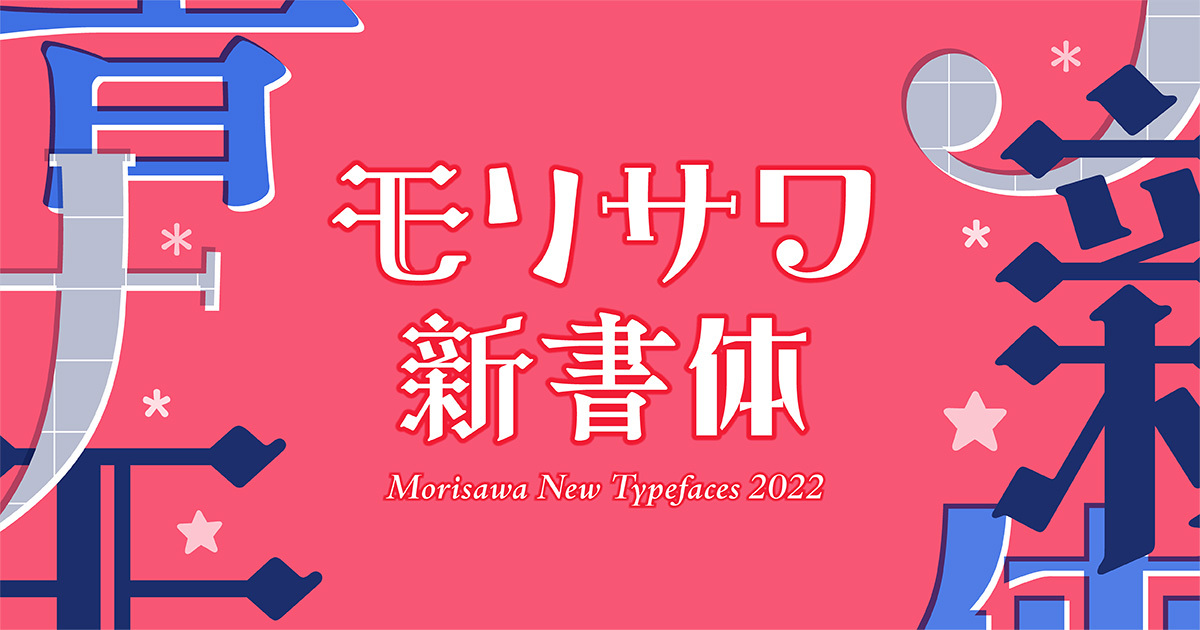
モリサワが10月26日(水)11時から2022年新書体の提供を開始。2022年新書体の特設ページが9月27日に公開
モリサワは、2022年10月26日(水)11時から「Morisawa FontsおよびMORISAWA PASSPORT アップグレード2022年10月版」として2022年新書体の提供を開始することを発表した。
「Morisawa FontsおよびMORISAWA PASSPORT アップグレード2022年10月版」では、合計77ファミリー500書体以上に及ぶ、過去最大の書体数が登場。
和文書体では『インパクト』『ゆるポップ』『ロマン』『オールド』の4つのジャンルで個性的なデザイン書体などを強化するほか、欧文書体も『オーガニック&ディスプレイ』『クラシカル&スタンダード』『Roleスーパーファミリー』『Clarimo UDシリーズ』の4ジャンルを一挙にリリースする。
また、「秀英四号太かな」を「秀英初号明朝」の漢字と合わせて総合書体化した「秀英四号太かな+」や、ユニークでどこか懐かしい書体「ヒラギノ丸ゴ オールド」も登場。
さらに今回の新書体提供にあわせて、「リュウミン」、「ゴシックMB101」、「すずむし」をはじめとした人気書体のAP版や、「G2サンセリフ」の文字セット追加、定番書体「こぶりなゴシック」のウエイトも追加される。
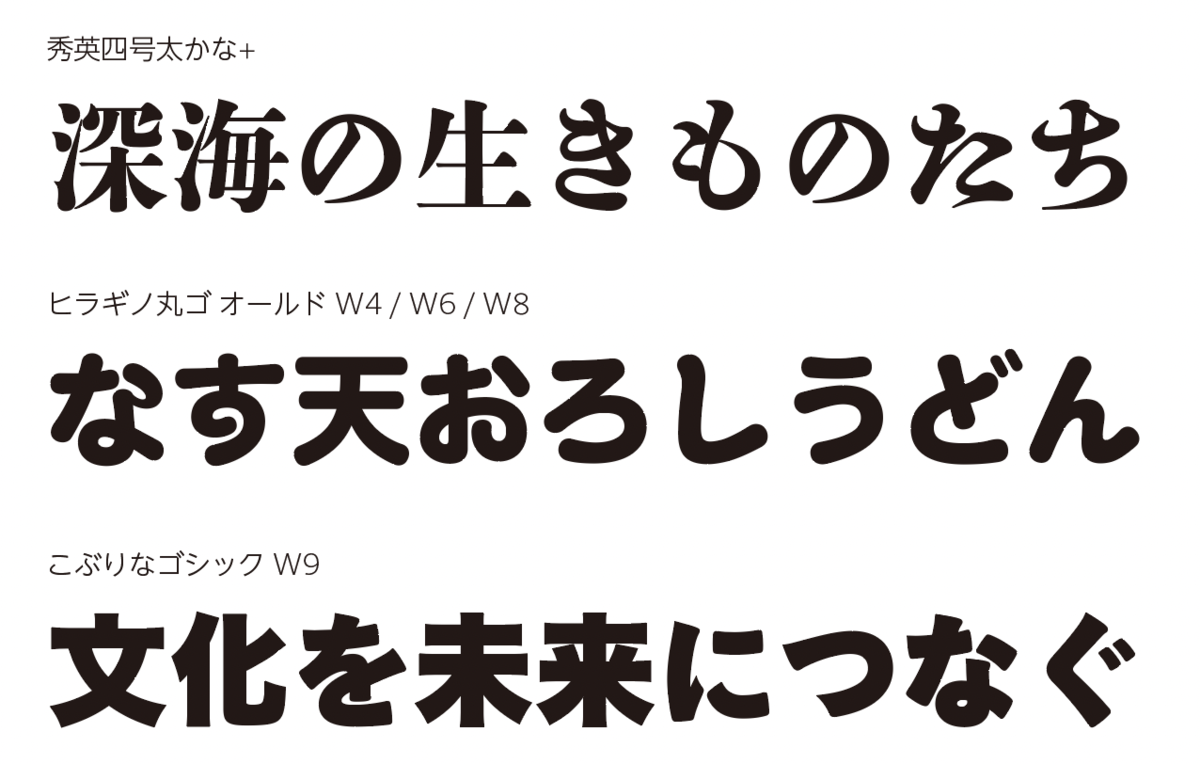
モリサワ2022年新書体特設ページが9月27日に公開
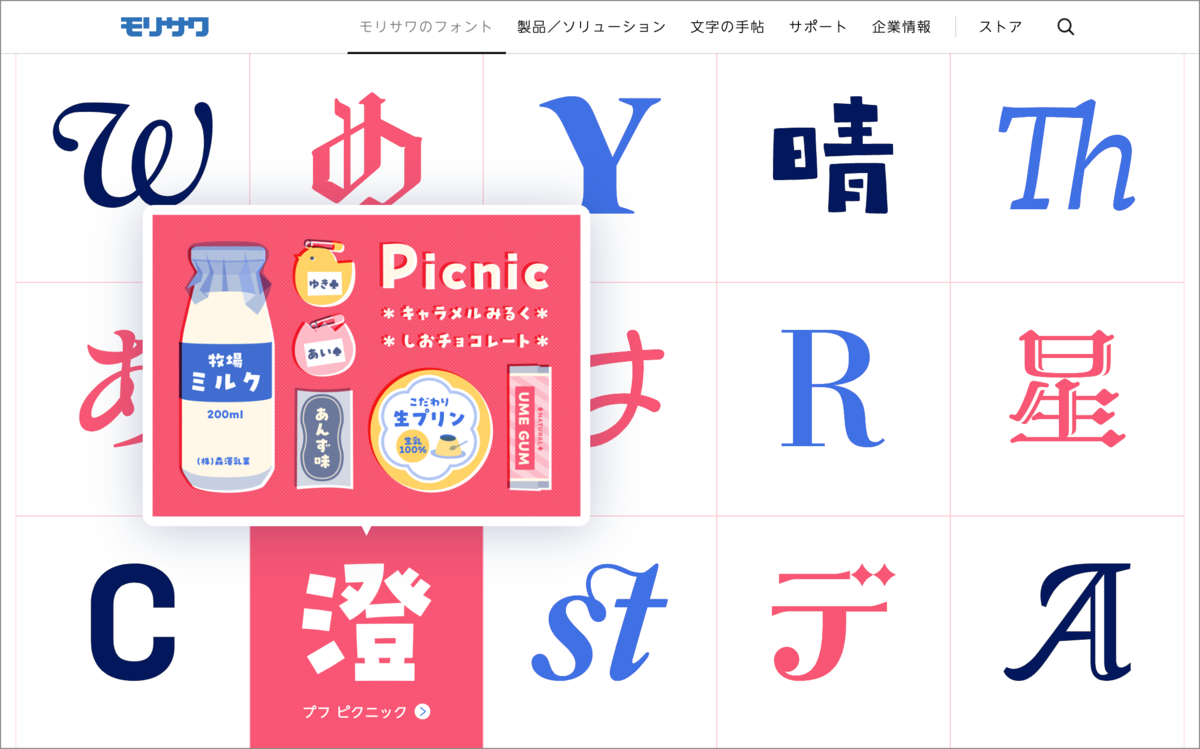
モリサワ2022年新書体特設ページが9月27日(火)にで公開された。
それぞれの書体の特徴や組見本を多数掲載し、使用イメージが提案されたページになっている。
モリサワ公式notでも各書体の特徴解説やおすすめの使い方などを紹介。
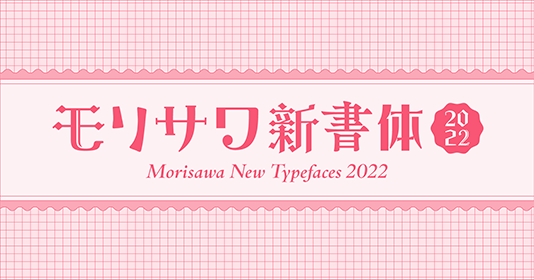
▼新書体一覧
〈和文書体〉
▼インパクト
イカヅチ、くろまめ、翠流アトラス、ラピスエッジ、ラピスメルト
▼ゆるポップ
ココン、タカ風太、ちさき、ぽってり、プフ ホリデー、プフ ポッケ、プフ マーチ、プフ ピクニック
▼ロマン
オズ、白のアリス、翠流ネオロマン、翠流デコロマン
▼オールド
霞青藍、霞白藤、白妙、白妙 オールド、秀英にじみ四号太かな、文游明朝体 古雅かな、文游明朝体S 朝靄かな、文游明朝体S 水面かな、ヒラギノ丸ゴ オールド
▼その他
こぶりなゴシック、G2サンセリフ
〈欧文書体〉
▼オーガニック&ディスプレイ
Abelha Pro
Areon Pro
Concert Pro
Eminence Pro
LatinMO Pro / LatinMO Condensed Pro
Lima PE
Pistilli Pro
Rocio Pro
Tapir Pro
Vonk Pro
Zingha Pro
▼クラシカル&スタンダード
BodoniMO Pro / BodoniMO Condensed Pro
CaslonMO Pro / CaslonMO Condensed Pro / CaslonMO Compressed Pro
Cetra Text Pro / Cetra Display Pro
Letras Oldstyle Pro / Letras Oldstyle Narrow Pro / Letras Oldstyle Condensed Pro
Pietro Text Pro / Pietro Display Pro
Prelude Pro / Prelude Condensed Pro / Prelude Compressed Pro
Star Times Text Pro / Star Times Display Pro
VibeMO Pro / VibeMO Condensed Pro / VibeMO Compressed Pro
▼Roleスーパーファミリー
Role Serif Text Pro / Role Serif Display Pro / Role Serif Banner Pro
Role Sans Text Pro / Role Sans Display Pro / Role Sans Banner Pro
Role Slab Text Pro / Role Slab Display Pro / Role Slab Banner Pro
Role Soft Text Pro / Role Soft Display Pro / Role Soft Banner Pro
▼Clarimo UDシリーズ
Clarimo UD PE Narrow / Clarimo UD PE Condensed / Clarimo UD PE Extra Condensed / Clarimo UD PE Compressed / Clarimo UD PE Extra Compressed
※1「G2サンセリフ」は文字セットを拡張、「こぶりなゴシック」および「Vonk Pro」はウエイトを追加。
※2「Rocio Pro」は、2016年提供の「Rocio」「Rocio Italic」とは異なる文字セットを採用。
〈総合書体化〉
秀英四号太かな+、ハッピーN+、丸ツデイ+、丸アンチック+、カモレモン+、カモライム+
〈AP版〉
リュウミン、太ミンA101、見出ミンMA1、見出ミンMA31、ゴシックMB101、中ゴシックBBB、太ゴB101、見出ゴMB1、見出ゴMB31、トーキング、武蔵野、プリティー桃、すずむし、新正楷書CBSK1、欧体楷書、楷書MCBK1、教科書ICA、角新行書、隷書E1、隷書101、陸隷、勘亭流